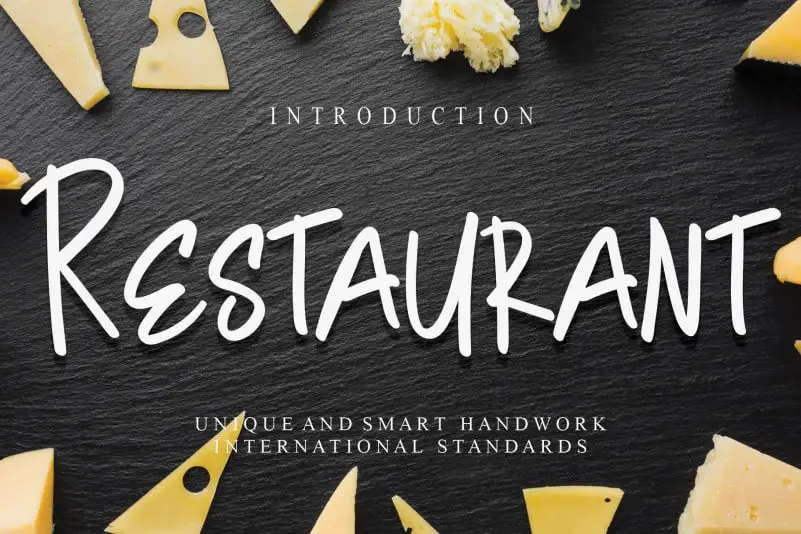
Restaurant Display Font – Download Grátis
Esta fonte ‘Restaurant Display Font’ da categoria Playful é criada para aqueles que querem imprimir uma atmosfera relaxante e alegre na decoração do seu restaurante, bar ou café. Com linhas levementes e formas arredondadas, essa fonte ajuda a transmitir um toque de descontração e hospitalidade ao público que entra. Seja para marcar o nome da sua casa de refeições em um menu, na entrada de seu estabelecimento ou até mesmo em uma cartaz promocional, esta fonte convida a uma experiência única para os clientes. Ela é perfeitamente adaptada para criar uma sensação de conforto e leveza que é tão valorizada no ambiente gastronômico. Através deste design, sua marca pode se destacar com estilo enquanto inspira seus visitantes a se sentirem em casa. Desenvolvida pelo designer creativletter, esta fonte apresenta detalhes cuidadosamente criados para oferecer uma experiência visual inigualável ao seu público. Ela é perfeita para aqueles que desejam transmitir um toque de humor e descontração através da design, e pode ser a escolha ideal para estabelecimentos onde a hospitalidade e a amabilidade são valores centrais.